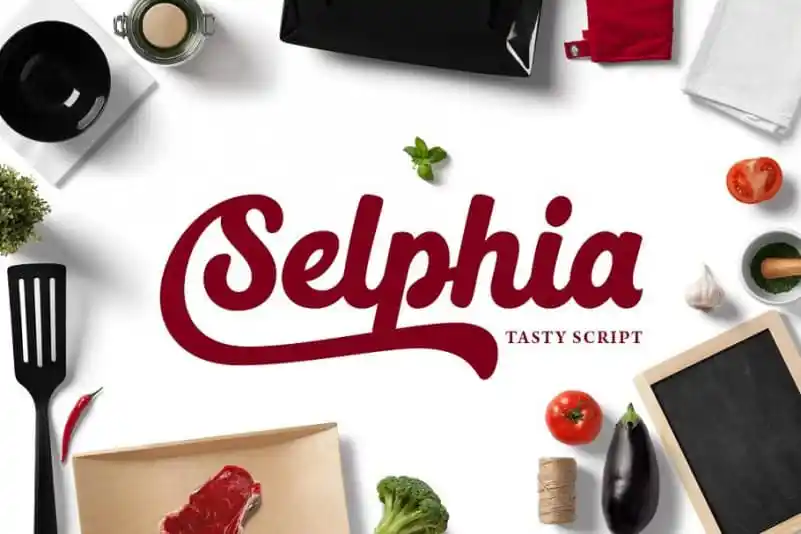
A Selphia Script Font é uma tipografia script minimalista que oferece um toque delicado e sofisticado à sua criação. Suas linhas elegantes e seu design limpo criam uma aparência confortável e envolvente, tornando-a perfeita para qualquer projeto de texto. A Selphia Script Font transmite um charme casual que a torna extremamente versátil – ela se adapta perfeitamente tanto aos elementos visuais como ao conteúdo do design. Idealmente usada em aplicações OpenType, como Adobe Illustrator, Adobe InDesign ou CorelDraw X6, esta fonte pode ser facilmente personalizada com o uso de alternativas e recursos de opentype. Suas nuances sedosas e suas influências cítricas e leitescas fazem dela uma opção perfeita para design de rótulos, logos, camisetas ou até mesmo criações de citações. Além disso, por se tratar de uma fonte script, ela é ideia para criar um ambiente acolhedor em qualquer projeto de marca. A Selphia Script Font não apenas é versátil, mas também encanta pelo seu design delicado e pela sua capacidade única de adaptar-se a diversos estilos, tornando-a uma escolha inteligente para quem busca tanto beleza quanto flexibilidade na criação do seu próximo design.